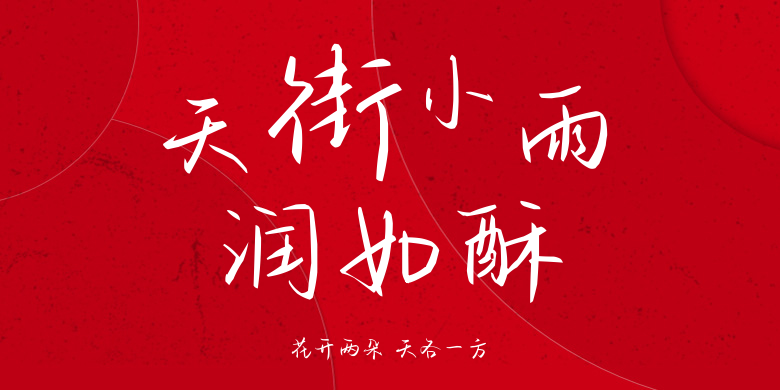
花开两朵 天各一方
花开两朵 天各一方,这款字体结构工整、笔画清晰,兼顾美观与易读性,适用于标题、正文、海报、包装、LOGO 等多种场景。字形优雅稳定,风格百搭耐看,适配日常排版与创意设计,让文字呈现更舒适、更具质感。花开两朵 天各一方一笔一画,皆是细节,以均衡的比例、流畅的线条打造舒适视觉体验,字形端正大气,风格简约现代。无论是商业设计、品牌宣传还是日常排版,都能轻松驾驭,让文字更有格调与力量。花开两朵 天各一方字体下载。